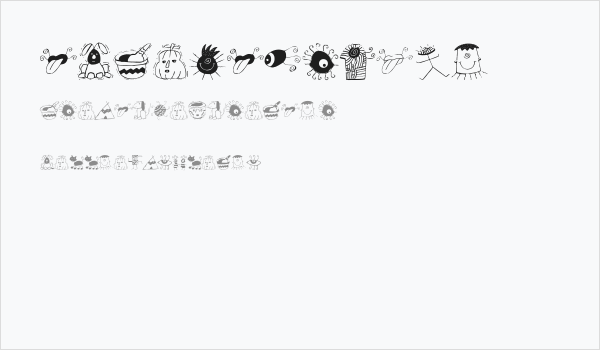
20thCenturyTwo Font
| 全体的なスタイル | Whimsical, Playful, Creative |
| 用途 | Artistic projects, Creative branding, Informal designs |
| おすすめプロジェクト | Children's books, playful branding, artistic projects, creative invitations, educational materials. |